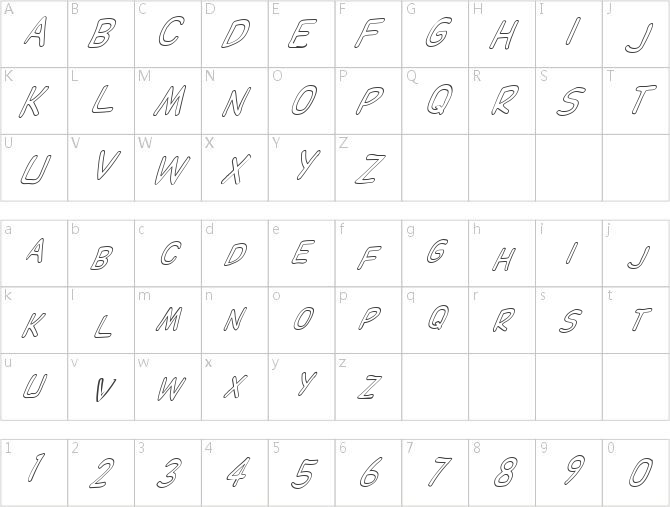
FZ BASIC 29 HOLLOW ITALIC 詳情頁
FZ BASIC 29 HOLLOW ITALIC字體字庫是一款讓人賞心悅目、百看不厭的英文字體,適合各類廣告和產(chǎn)品包裝設(shè)計(jì)應(yīng)用,字體大小0.09MB,格式為ttf字體,上傳用戶是Honor,作者/版權(quán)方為未知